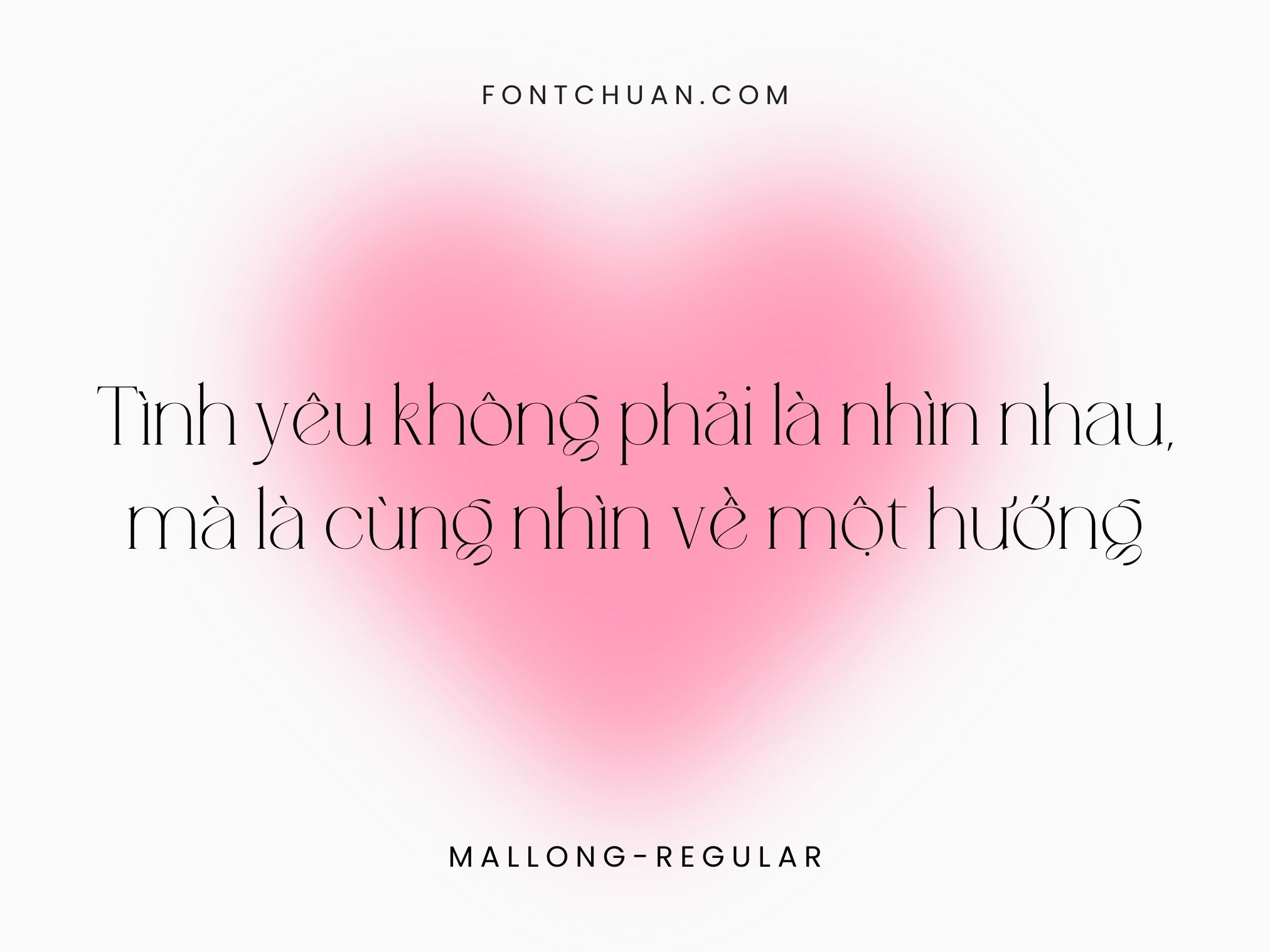
Font Mallong Regular Việt Hóa
Tác giả Font: Kana Widana
Mallong là một font serif mang phong cách thanh lịch và tự nhiên, được thiết kế bởi Alit Design. Với sự kết hợp giữa các chi tiết serif cổ điển và đường cong mềm mại, font này mang đến vẻ đẹp tinh tế và sang trọng. Mallong hỗ trợ tiếng Việt và nhiều ngôn ngữ khác, được sưu tầm và đăng bởi thành viên của Font Chuẩn.
Với cấu trúc chữ rõ ràng, độ dày nét đồng nhất và các đường nét uyển chuyển, Mallong không chỉ là một Font Display lý tưởng cho các tiêu đề và ấn phẩm nổi bật mà còn là một Font chữ thiệp cưới tinh tế, mang đến vẻ đẹp mềm mại, trang nhã cho thiệp mời, thiệp chúc và các sản phẩm in ấn dành cho các dịp đặc biệt. Font này phù hợp cho các ứng dụng như thiết kế thiệp cưới, logo, tiêu đề và các ấn phẩm truyền thông. Các ngành nghề như quảng cáo, thiệp cưới, giáo dục và bất động sản có thể tận dụng hiệu quả Mallong để tạo điểm nhấn độc đáo. Ngoài ra, font cũng thích hợp cho các sự kiện như lễ hội, sinh nhật, ngày Nhà giáo và Valentine, mang đến không khí sang trọng và tinh tế.